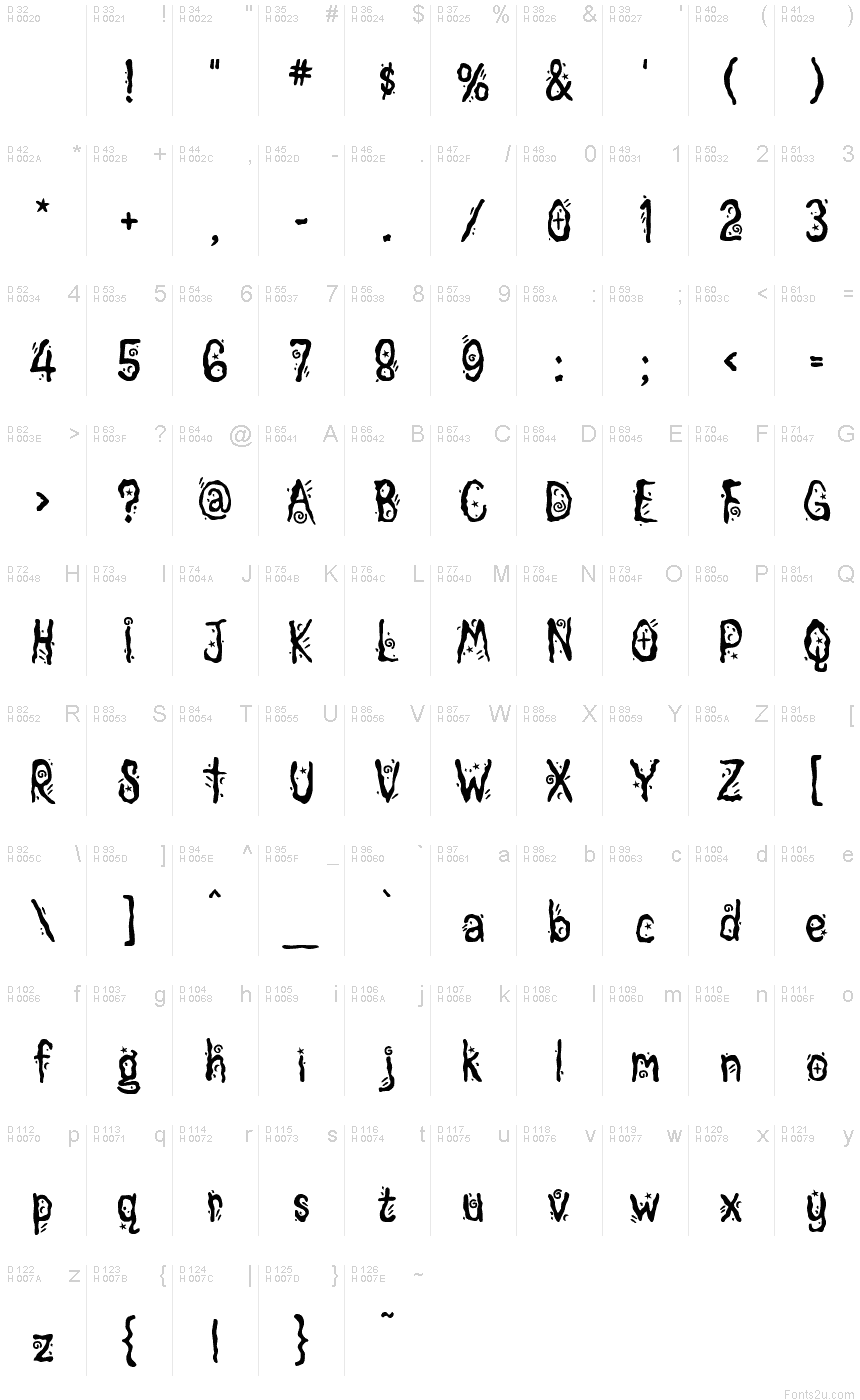
Magician
Magician to darmowy, ręcznie rysowany font typu display, który czerpie inspirację z magii estradowej. Litery wyglądają, jakby zostały namalowane pędzlem i oprószone drobnymi gwiazdkami. Cały alfabet sprawia wrażenie nieco rozchwianego i zaczarowanego – zamiast surowej precyzji mamy tu nierówne krzywe, zwężające się pociągnięcia i wyraziste sylwetki, które nadają projektowi zabawny, lekko okultystyczny charakter.
Dzięki temu ten darmowy font jest naturalnym wyborem na plakaty na Halloween, ulotki imprezowe, okładki książek dla dzieci, nietuzinkowe opakowania czy szyldy sklepowe, które mają przywoływać klimat domowego księgi zaklęć. Wykorzystaj go w krótkich nagłówkach, tytułach czy monogramach, gdzie gwiazdkowe akcenty i nieregularny rytm robią wrażenie nawet bez dużej ilości tekstu.